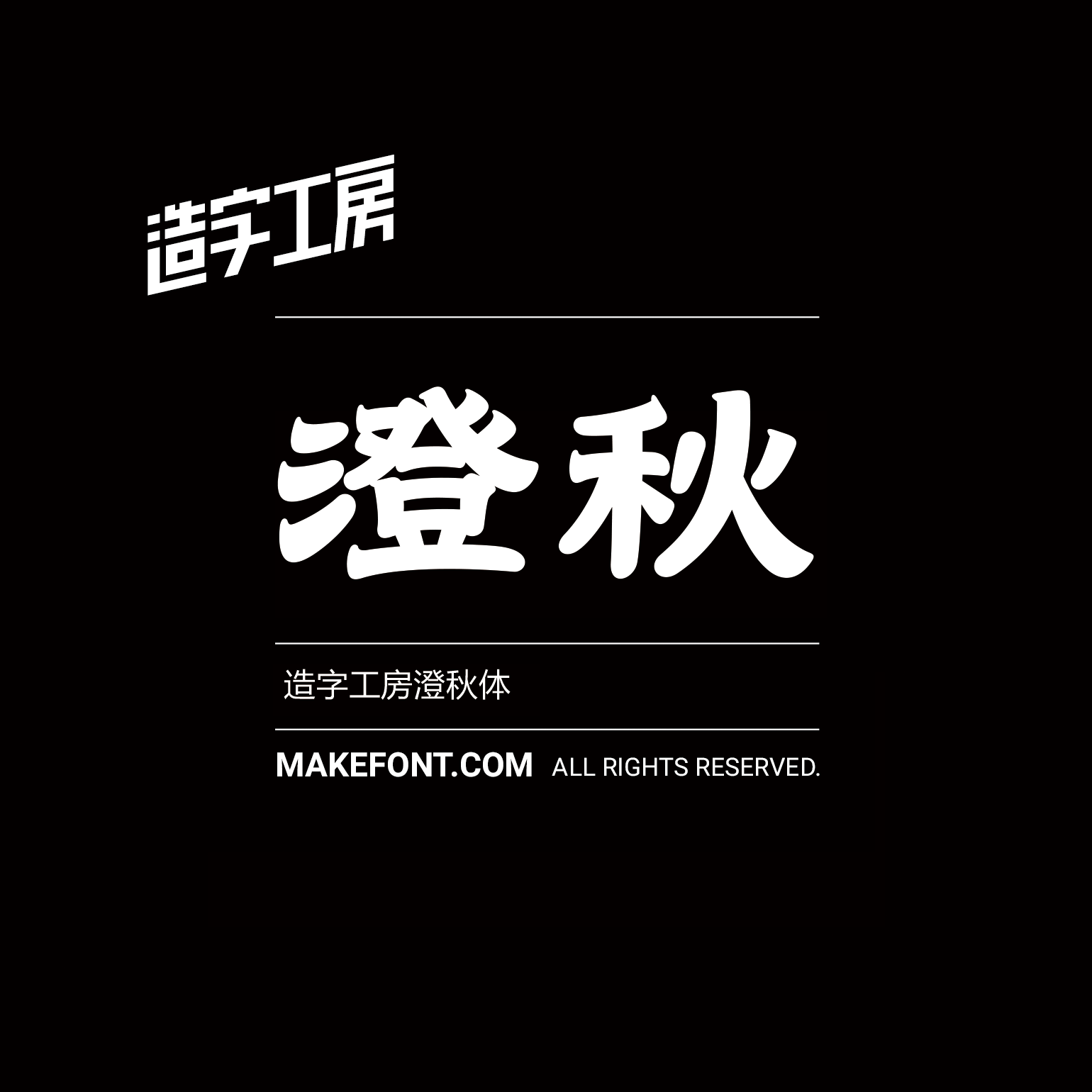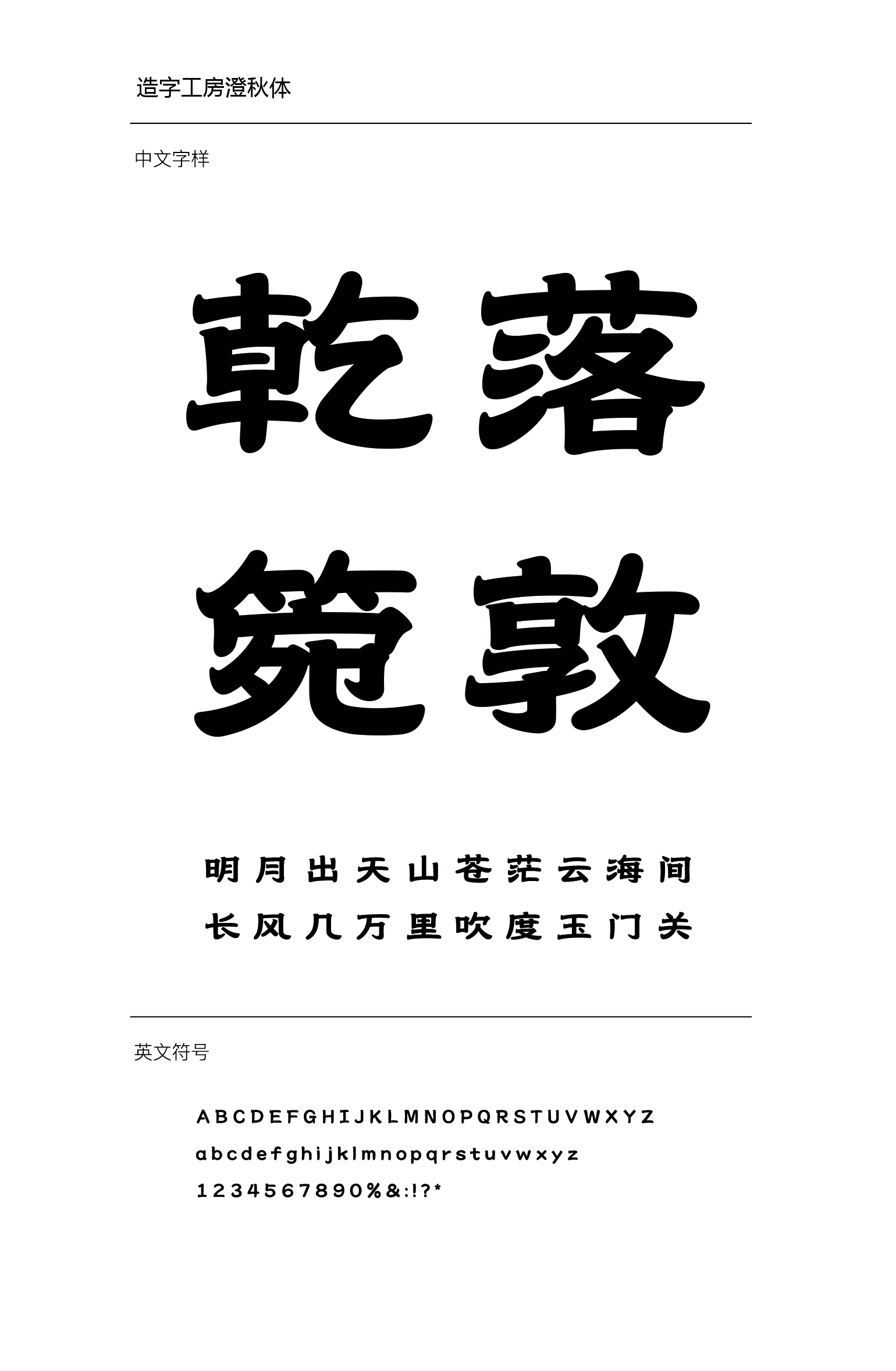
造字工房澄秋体设计说明
造字工房澄秋体,以隶书为基础,笔画长短、曲直遵循结构规律,字形紧凑均匀、飘逸流畅;线条走势跌宕有致;起笔俏皮生动,收笔沉稳大气;笔触行云流水,断连辗转、粗细藏露间皆变化万千,是一款兼具“风神骨气”的古典审美设计与现代浪漫气质的全新字体。适用于艺术作品,平面海报,广告设计推广等环境。本字体为简体字库,采用OpenType/CID格式,Adobe-GB1-5编码。基于中华人民共和国GB2312-80字符集标准,另按需添加101个汉字。共收容字数6864CJK汉字,ASCII常用字符100个。